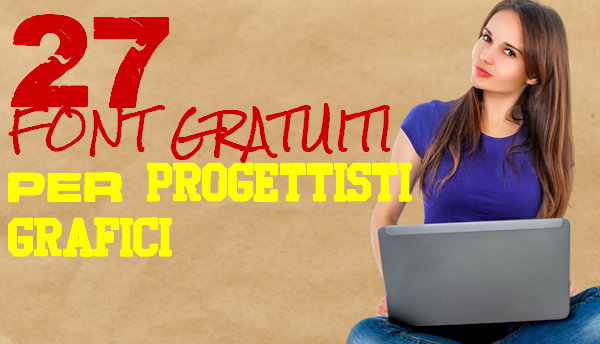
I font selezionati sono di alta qualità , e sono adattabili per qualsiasi tipo di lavoro di grafica.
Tutti i font della collezione sono utili per loghi, citazioni, progettazione di giornali e poster.
27 font gratuiti per progettisti grafici